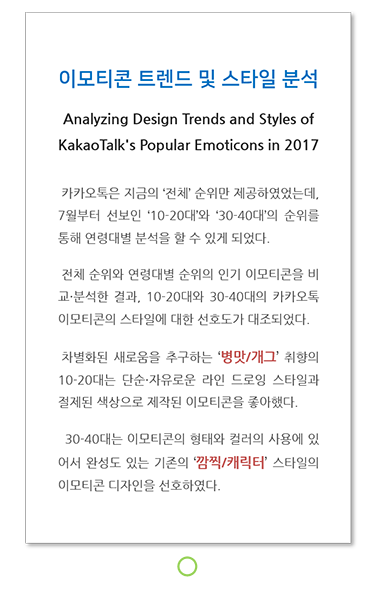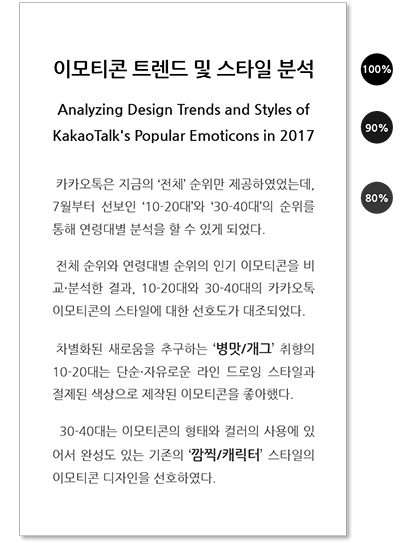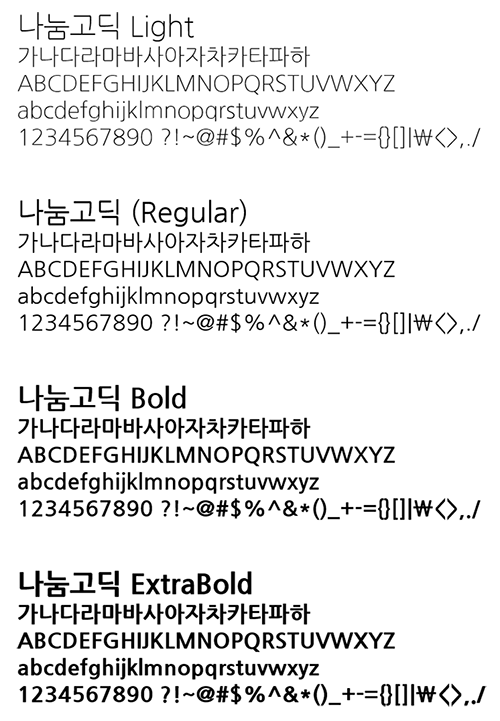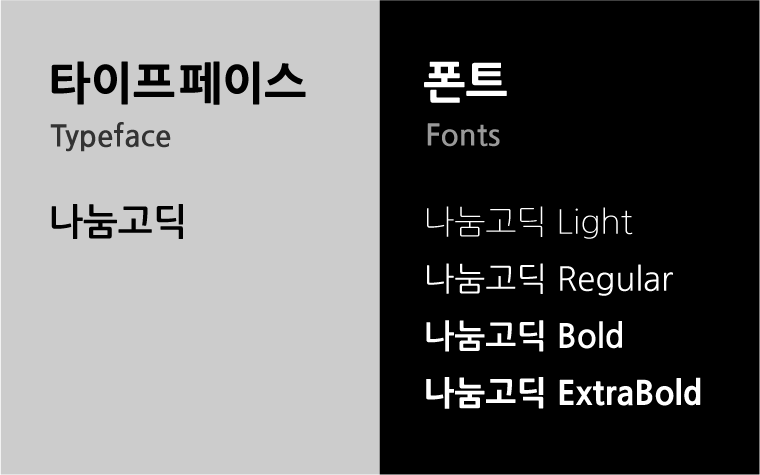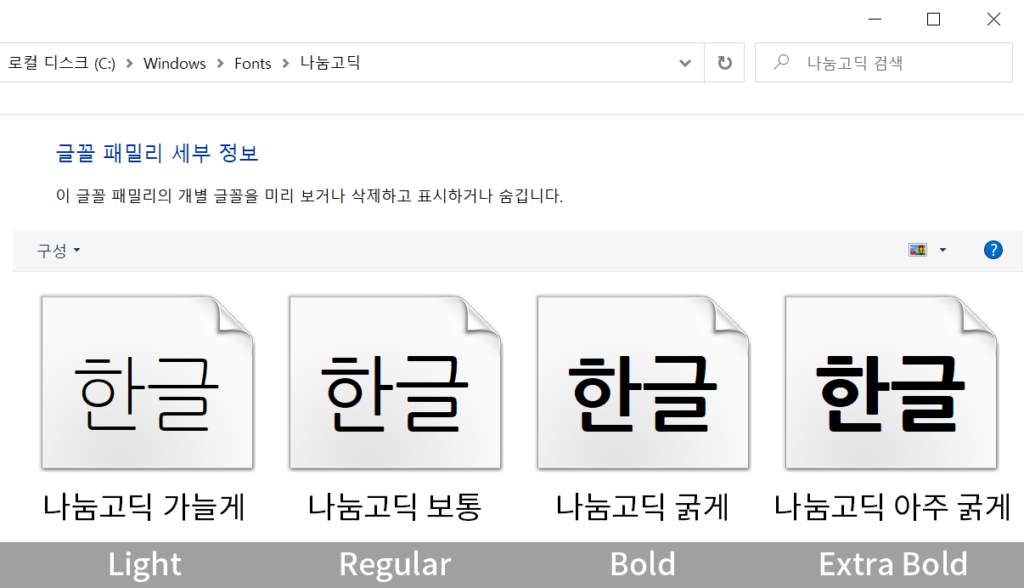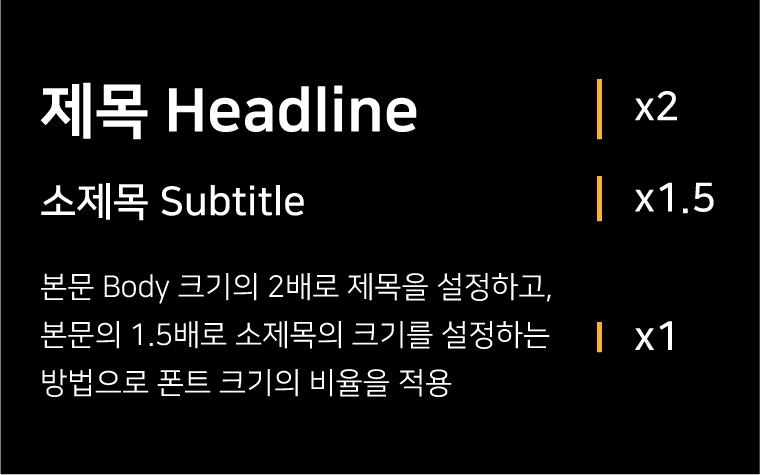
“TIP! 01. 컬러와 폰트는 1~2개만 사용하자!“에서 하나의 폰트, 즉 폰트 패밀리 개념인 타이프페이스(Typeface)를 하나만 사용해서 좋은 디자인을 하는 방법에 대해서 알아보았습니다.
이번에는 일반적으로 호칭하는 폰트 하나, 즉 1개의 타이프페이스를 사용해서 디자인 방법 중 대비(Contrast) 효과를 적용하여 디자인의 통일성을 유지하면서 변화를 주는 방법에 대해서 알아보도록 하겠습니다.
1. [무게 대비] 타이프페이스(Typeface)의 폰트 굵기 속성을 활용하세요.
2. [크기 대비] 폰트의 크기를 역할에 맡게 조절해주세요.
3. [색상 대비] 1개의 컬러로 강조하고, 검은색의 변화를 적용하세요.
4. [모양 대비] 필요하면 비슷한 스타일의 폰트를 추가하여 변화를 주세요.
1. [무게 대비] 타이프페이스(Typeface)의 폰트 굵기 속성을 활용하세요.
타이프페이스 vs 폰트
(Typeface vs Fonts)
여러분은 보통 폰트를 사용 후 다음과 같이 말할겁니다. “나눔고딕 폰트를 사용했습니다!”
하지만 이는 반은 맞고, 반은 틀린 것으로 좀 더 정확히 얘기하자면 “나눔고딕 타이프페이스(Typeface)를 사용했습니다!”라고 말하는 것이 정확합니다.
물론 디자이너들도 현실에서는 ‘폰트’와 ‘타이프페이스’ 두 용어를 혼용해서 사용하긴 합니다.^^;
윈도우 시스템상의 나눔고딕 글꼴 패밀리 세부 정보
윈도우 시스템에서 폰트 중 나눔고딕을 찾아보면 위의 그림과 같이 ‘나눔고딕 가늘게(Light)’, ‘나눔고딕 보통(Regular)’, ‘나눔고딕 굵게(Bold)’, ‘나눔고딕 아주 굵게(ExtraBold)’가 한 세트로 구성되어 있습니다.
‘글꼴 패밀리 세부 정보’라고 나와 있듯이 타이프페이스는 폰트 패밀리로 ‘Light‘, ‘Regular‘, ‘Bold‘의 속성을 가진 폰트들의 한 세트로 구성되어 있습니다. 다시 말해 폰트의 속성 중 굵기에 따라 구분됩니다.
나눔고딕 타이프페이스(글꼴 패밀리)
일반적으로 지칭하는 폰트 한 개로도, 즉 하나의 타이프페이스를 사용해도 Light, Regular, Bold 등 굵기의 속성을 응용해서 디자인에 다양한 변화를 줄 수 있습니다.
예를 들어 글 또는 디자인에서 중요한 역할을 담당하는 제목과 키워드에 두꺼운(Bold) 폰트를 사용하는 것입니다.
위의 디자인에서 제목 “LAMB STEAK POTATO“를 보면 고딕체 스타일의 타이프페이스를 사용하고 폰트 획의 속성 중 굵기의 변화를 통해 표현하고 있습니다.
이렇게 하나의 타이프페이스를 사용하면서 폰트의 속성 중 굵기(Weight)를 잘 활용하면 디자인의 통일성을 유지할 수 있으면서 변화를 줄 수 있습니다. 비전공자와 디자인 초보자가 폰트를 디자인에 사용하는 데 있어서 안전하게 적용할 수 있는 한 방법입니다!
타이프페이스(Typeface)의 개념을 이해하고 적용할 수 있다면 당신은 이미 디자인 전문가입니다.^^
이러한 타이프페이스의 속성 중 Light, Regular, Bold 등의 폰트의 굵기를 활용하는 디자인 방법을 무게 대비(Weight Contrast) 또는 중량 대비라고 합니다.
2. [크기 대비] 폰트의 크기를 역할에 맡게 조절해주세요.
우리는 서류를 작성할 때 제목, 소제목, 본문의 폰트 크기를 다르게 적용합니다. 대부분 제목의 크기를 가장 크게 적용할 것입니다. 왜냐하면, 제목이 가장 중요한 역할을 담당하고 있기 때문입니다.
디자인 방법 중 일반적으로 제목, 소제목, 본문에 적용하는 크기의 비율이 있습니다. 본문이 10pt면 제목은 2배인 20pt로 설정하고, 소제목은 제목과 본문의 중간인 15pt를 적용합니다.
문장과 단락에서도 중요한 단어(Keyword)는 무게 대비로 두꺼운 폰트를 사용하면서 크기를 1.1~1.2배로 조금만 크게 하는 것도 강조해주면서 주목성을 높일 수 있는 디자인의 한 방법입니다.
이처럼 폰트를 적용하는 데 있어서 글 또는 디자인에서 담당하고 있는 역할에 맞춰 크기의 변화를 주는 대비 효과를 크기 대비(Size Contrast)라고 합니다.
디자인 트렌드(2021년도) 중 제목에 폰트를 굵게 그리고 특대형(Oversized)으로 적용하는 것이 유행입니다.
극단적인 크기 대비를 활용한 강조 효과를 통해 사용자에게 강한 인상을 심어주어 해당 미디어에 주목하게 하고 끌어들이기 위함입니다.
특대형의 제목을 사용할 때는 폰트 등 디자인의 구성요소를 심플하게 적용하는 것이 좋습니다!
3. [색상 대비] 1개의 컬러로 강조하고, 검은색의 변화를 적용하세요.
Kibana의 홈페이지 디자인을 보면 중요한 단어에 노란색을 사용하여 강조하였습니다. 이렇게 색으로 구별하여 디자인하는 방법을 색상 대비(Color Contrast)라고 합니다.
대비되는 컬러를 사용하여 해당 디자인 요소를 강조하는 방법에서는 주제색(Primary Color) 또는 강조색(Accent Color)을 정하고 적용하는 것이 좋습니다.
물론 주제색이든 강조색이든 1개의 색만 사용하는 것이 비전공자와 초보자에게 안전한 방법입니다.
디자인 시 간과하기 쉬운 것이 대부분 텍스트에 적용하는 검은색의 변화입니다.
검은색의 어둡기를 80% 정도 적용하면 회색으로 많이 밝아질 거라 생각되지만, 실제로는 어두운 회색(Dark Gray)으로 표현되어 알려주지 않으면 잘 모를 정도입니다.
위의 경우 제목에는 검은색 100%, 소제목에는 검은색 어둡기를 90%, 본문에는 80% 정도만 적용한 예입니다.
특히 디지털 환경에서는 본문의 경우 80% 정도의 어둡기를 적용한 검은색이 가독성을 높인다고 합니다.
이렇게 검은색의 밝기 조절을 통해 적용하는 방법(명도 대비)은 눈에 확연히 띄지는 않습니다. 하지만 이러한 작은 디테일을 적용하는 것이 좋은 디자인을 하는 방법이고 디자인 전문가가 많이 활용하는 방식입니다.
4. [모양 대비] 필요하면 비슷한 스타일의 폰트를 추가하여 변화를 주세요.
먼저 비전공자와 디자인 초보자는 타이프페이스 한 개를 적용하는 것을 추천합니다. 하지만 1개 정도 더 폰트를 추가하는 것도 디자인에 변화를 주는 방법이 됩니다.
단! 비슷한 모양의 폰트를 사용해주세요! 예를 들어 기존의 적용한 폰트의 스타일이 고딕체였을 경우에는 고딕체 계열로 적용하고, 명조체였으면 명조체 스타일의 폰트를 추가하는 것입니다.
위의 경우 제목에는 ‘나눔스퀘어 Bold’를 적용하고, 나머지는 ‘나눔고딕’을 사용한 예입니다. 이렇게 비슷한 스타일의 폰트를 적용하면 변화를 주면서도 통일성을 유지하는 전체적인 디자인의 일관성을 확보할 수 있습니다.
이렇게 다른 폰트를 사용하여 디자인의 변화를 주는 방법은 모양 대비(Shape Contrast)에 속합니다.